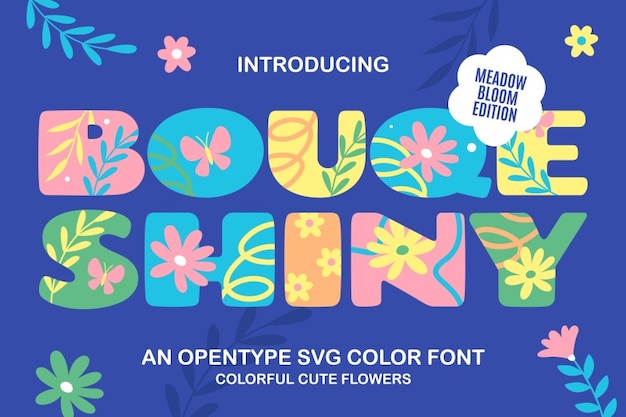
Bouqe Shiny
Bouqe Shiny Jenis Huruf
Bouqe Shiny adalah jenis huruf tampilan lembut yang terinspirasi bunga dengan gradien pastel dan tekstur ringan. Jenis huruf ini sangat cocok untuk kemasan bertema musim semi, branding kecantikan, atau karya kreatif yang ceria.